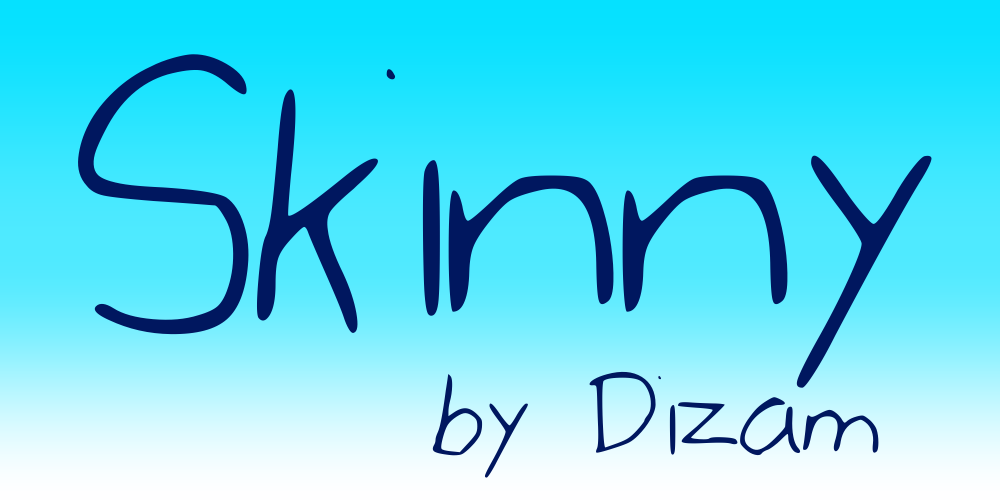
A SKINNY font oferece uma experiência visual única para designers digitais que desejam adicionar um toque pessoal a seus projetos de design. Criada pelo designer Hamilton, essa fonte é perfeita para quem busca uma mão escrita suave e envolvente, ideal para gráficos de email ou qualquer projeto que deseje transmitir um sentimento natural e autêntico. Com traços leves e linhas elegantes, a SKINNY captura nuances de escrita humana sem perder os detalhes técnicos essenciais. Seu estilo handwritten permite que seus projetos ganhem uma personalidade única, criando uma conexão direta com o público do design gráfico, oferecendo um toque único e envolvente à qualquer projeto. Ideal para designers que buscam incorporar elementos de escrita manual em suas criações digitais, a SKINNY é perfeita tanto para aqueles iniciantes quanto para os mais experientes, proporcionando uma ferramenta versátil para criar um design verdadeiramente autêntico e envolvente.